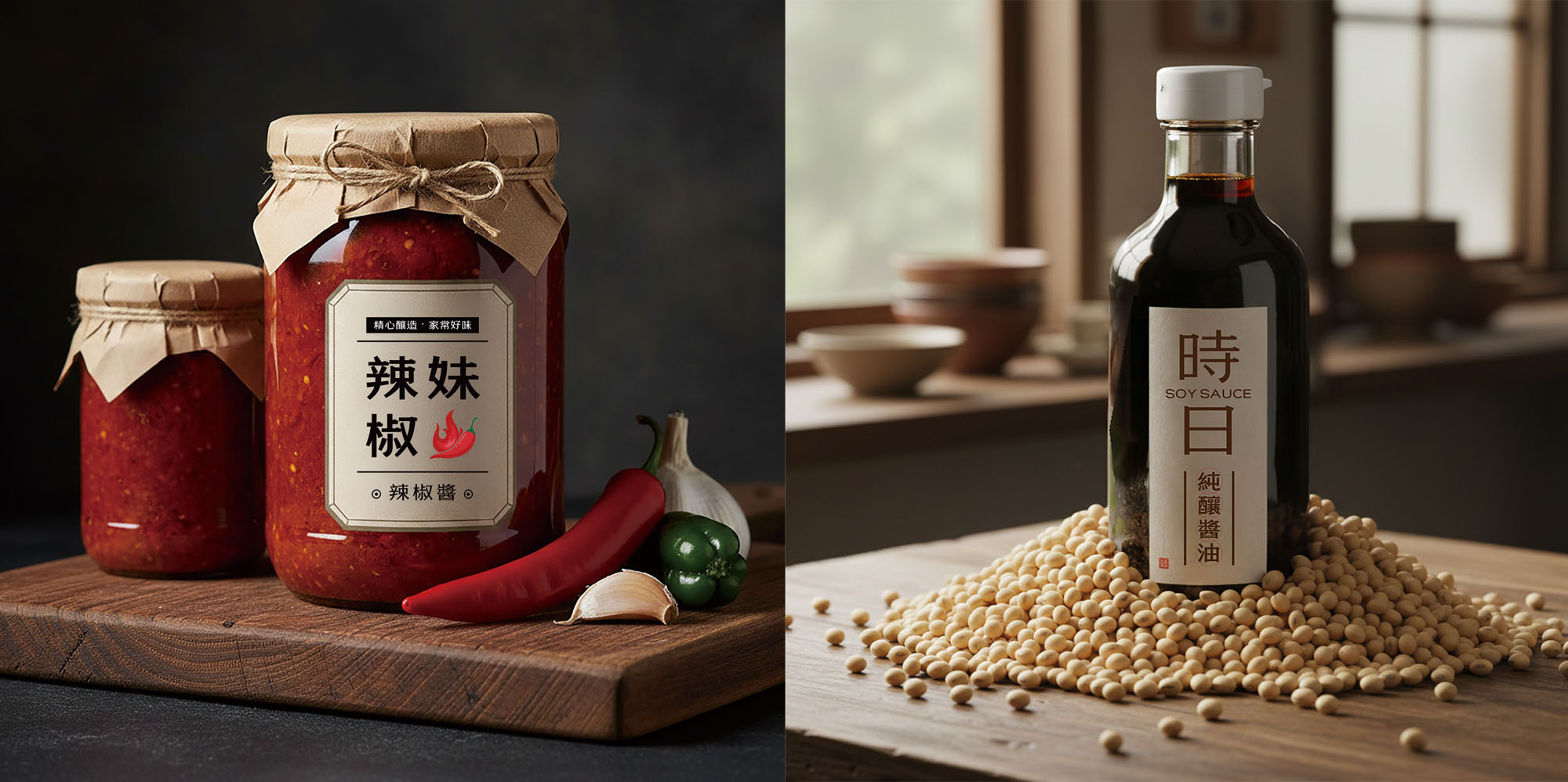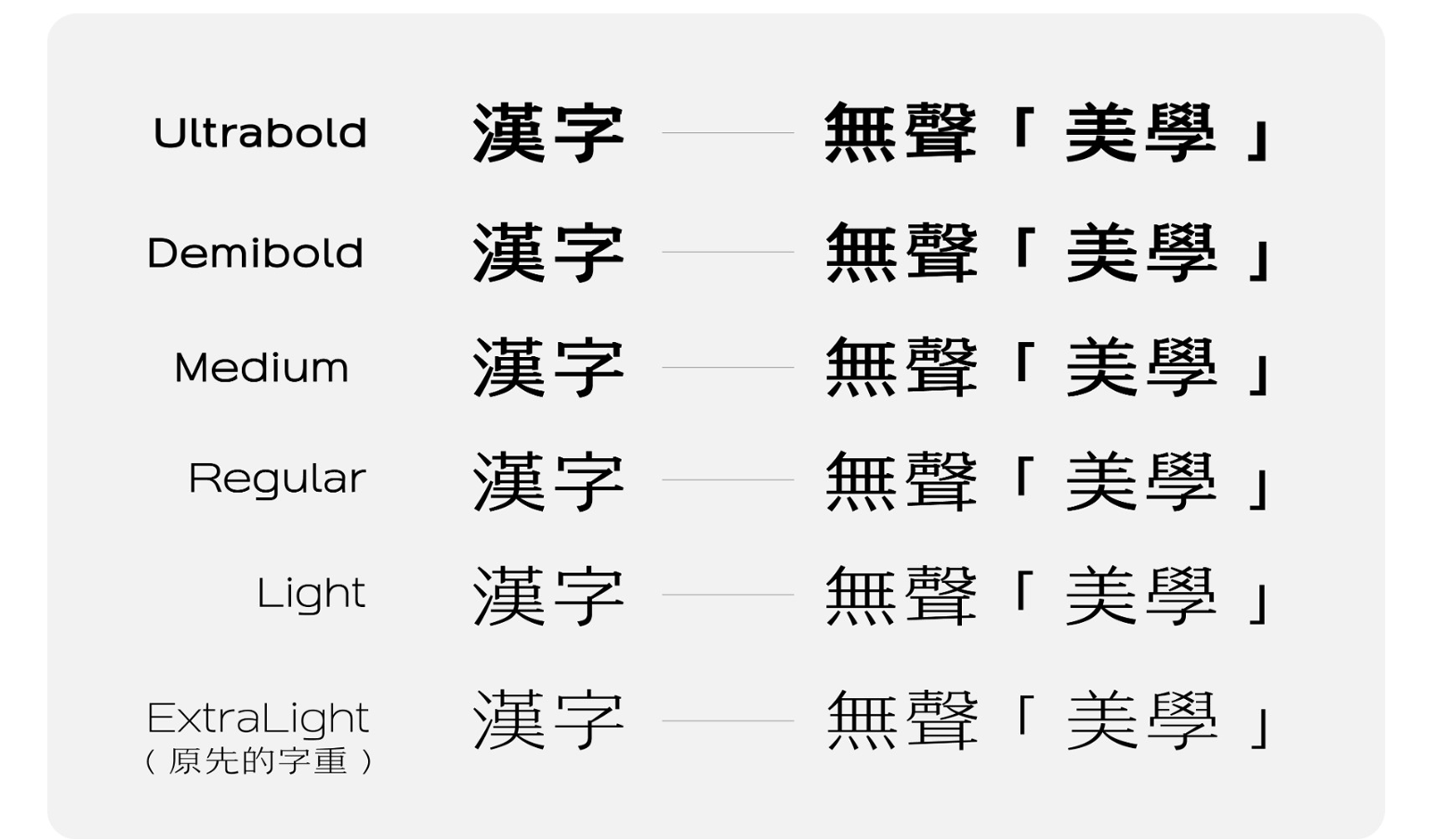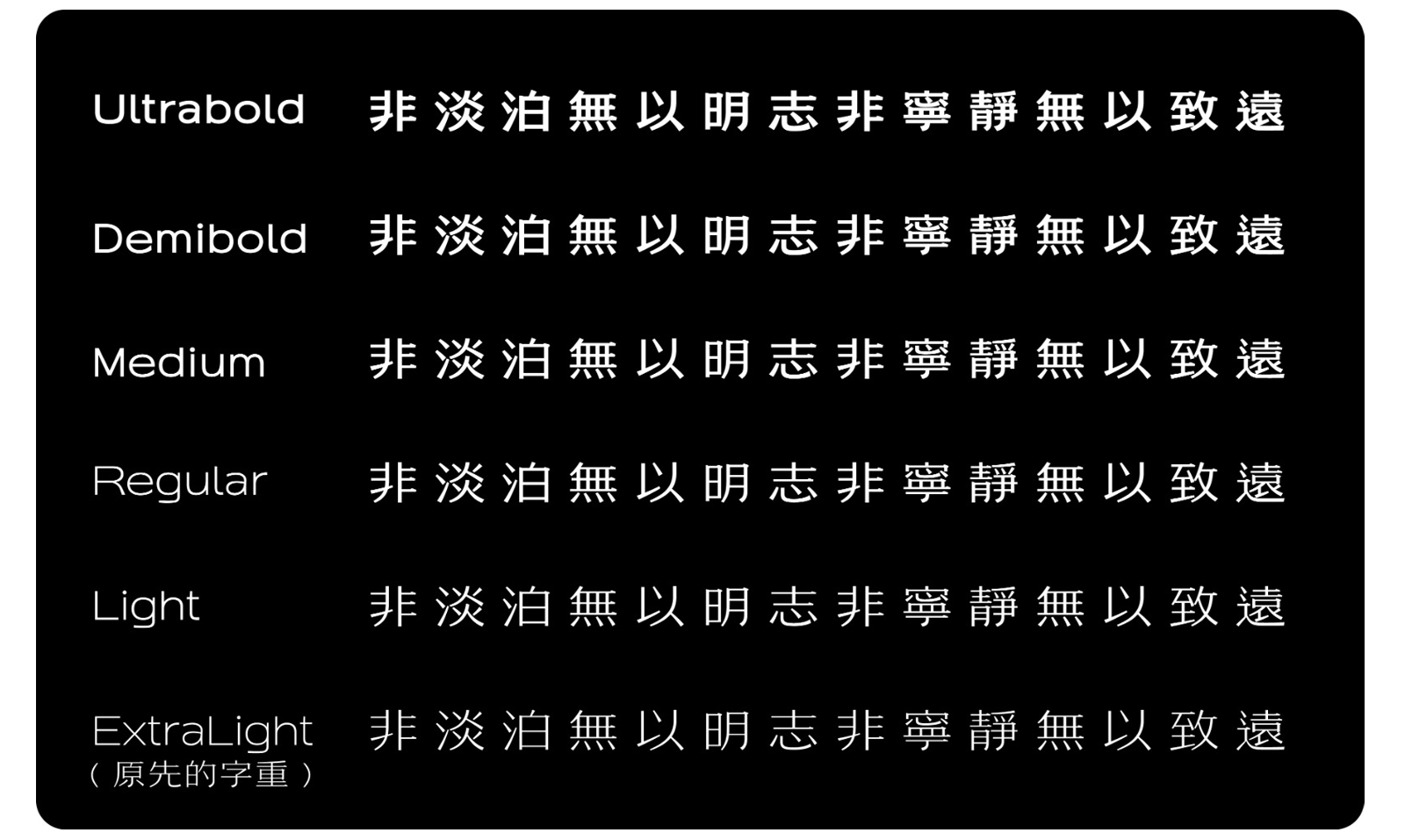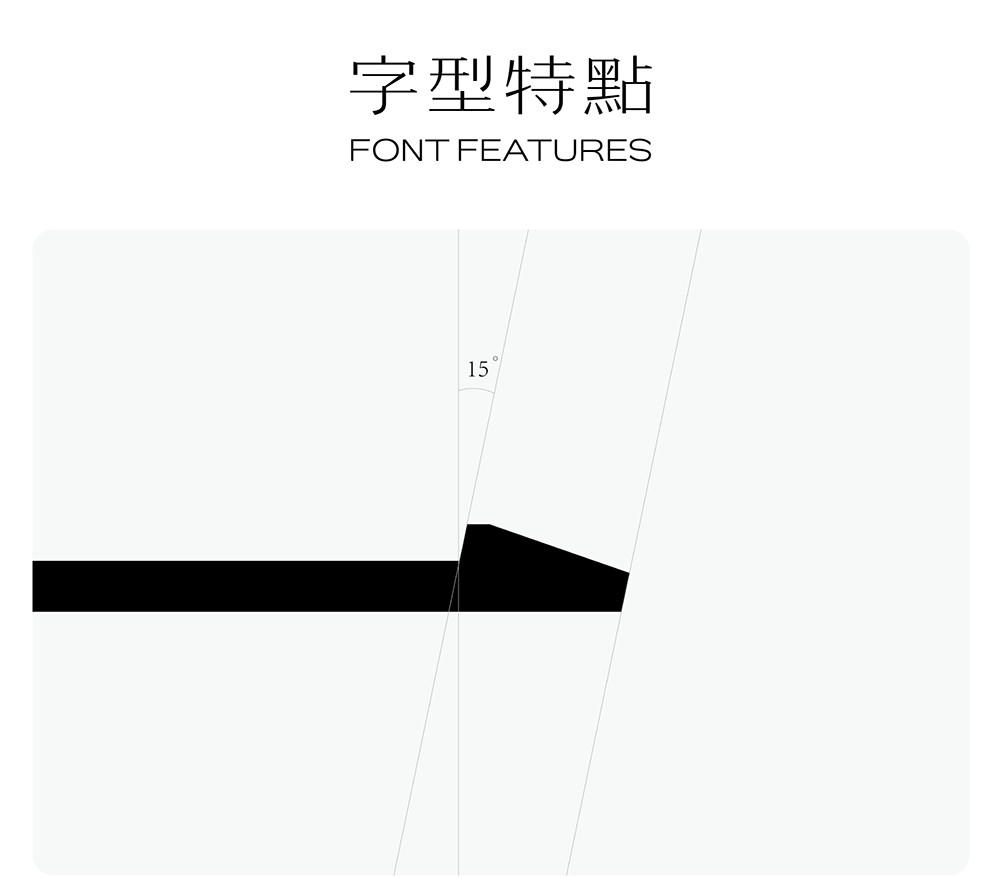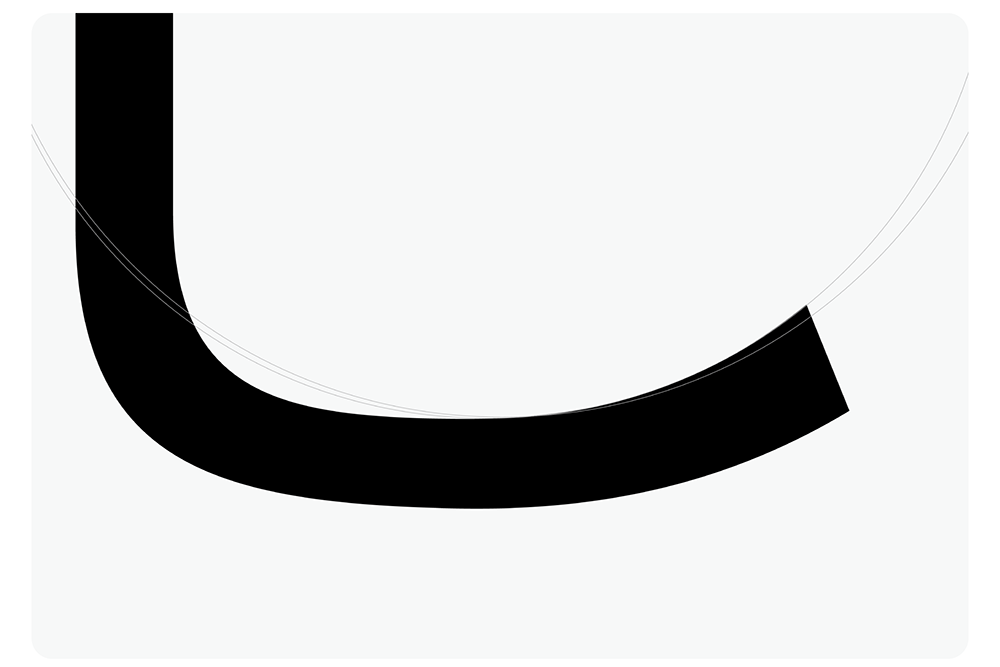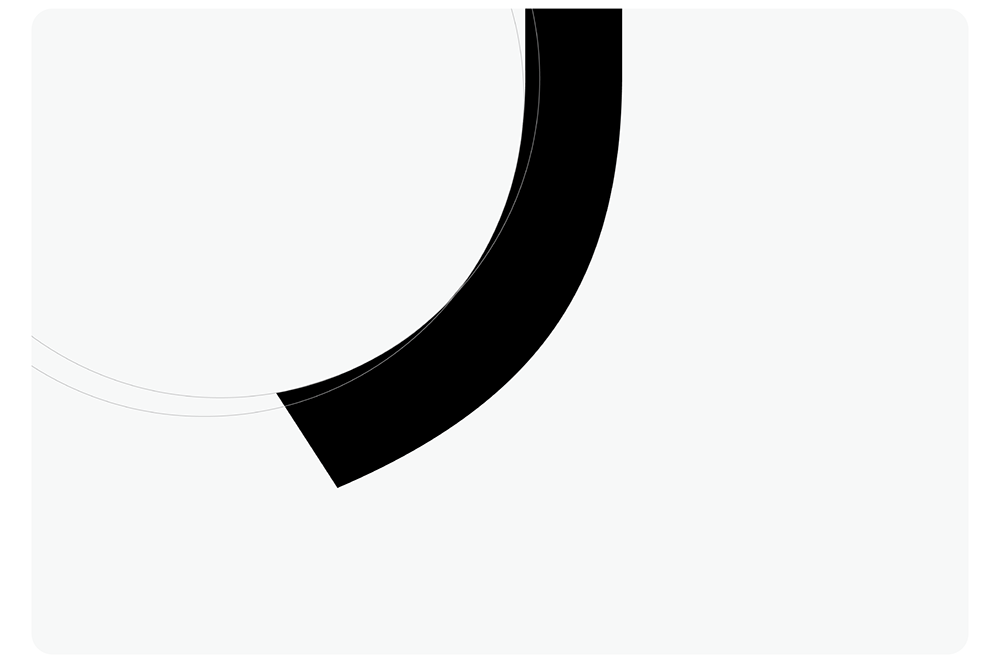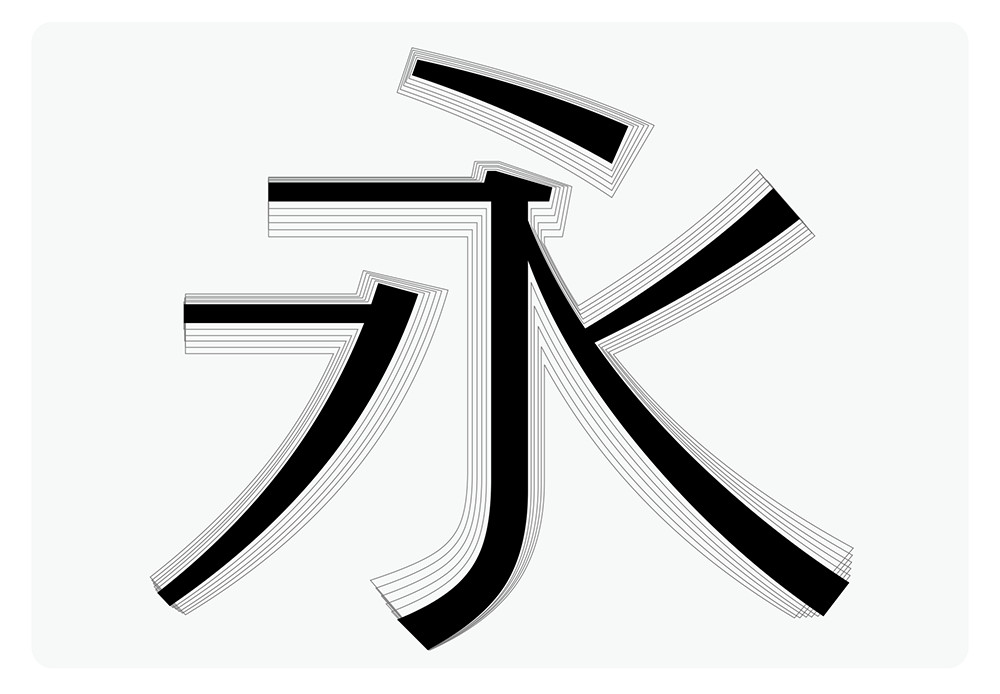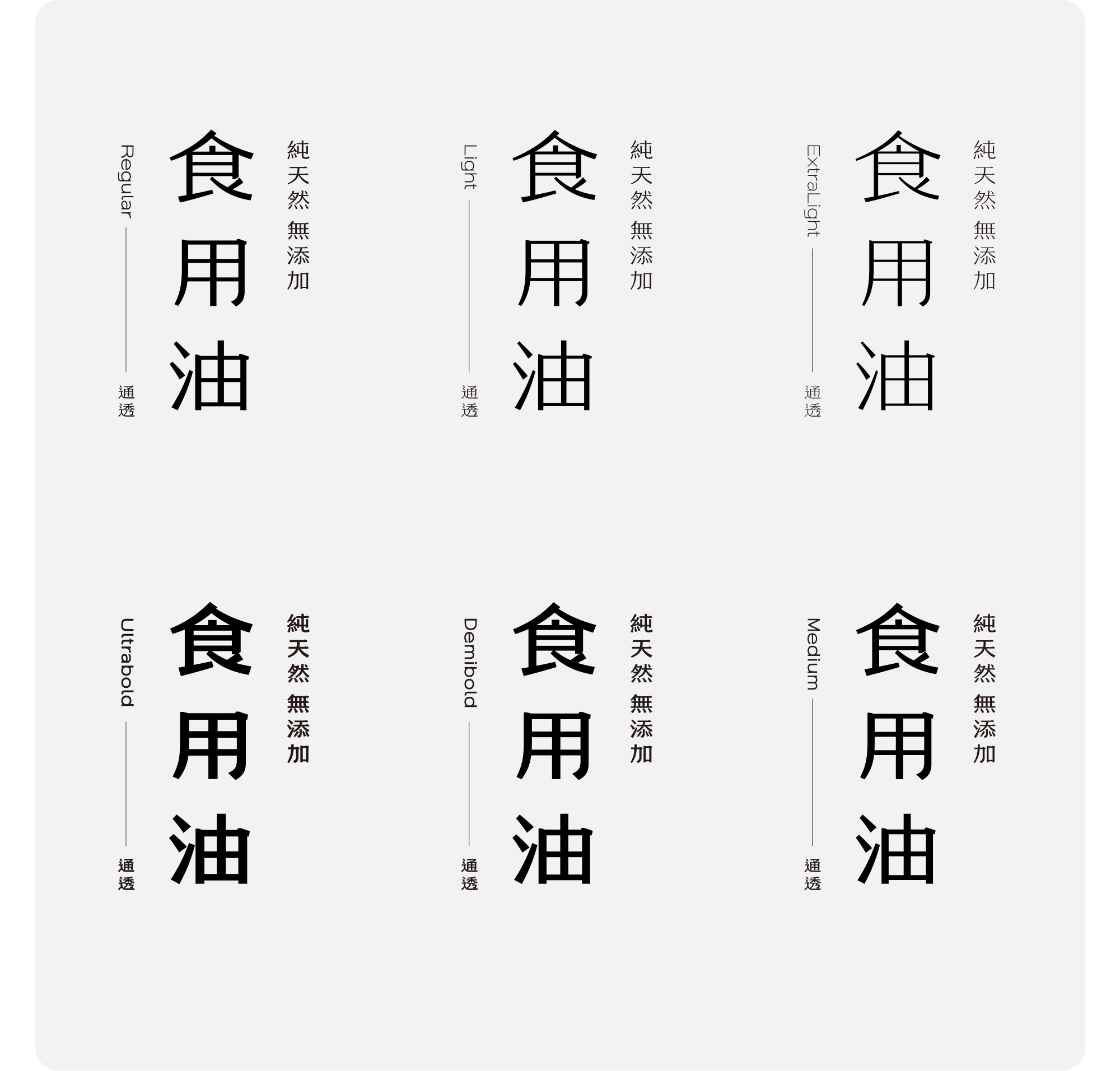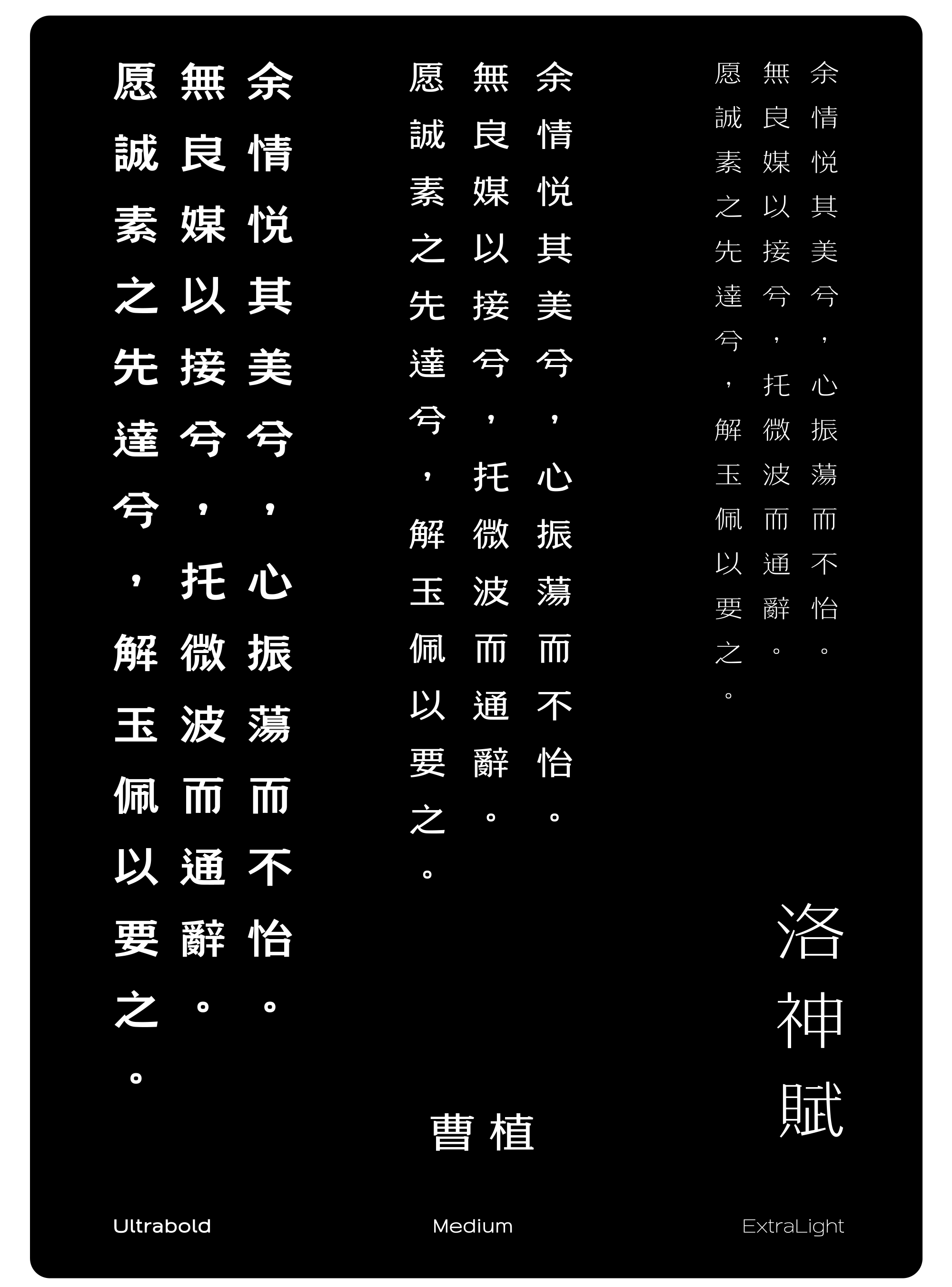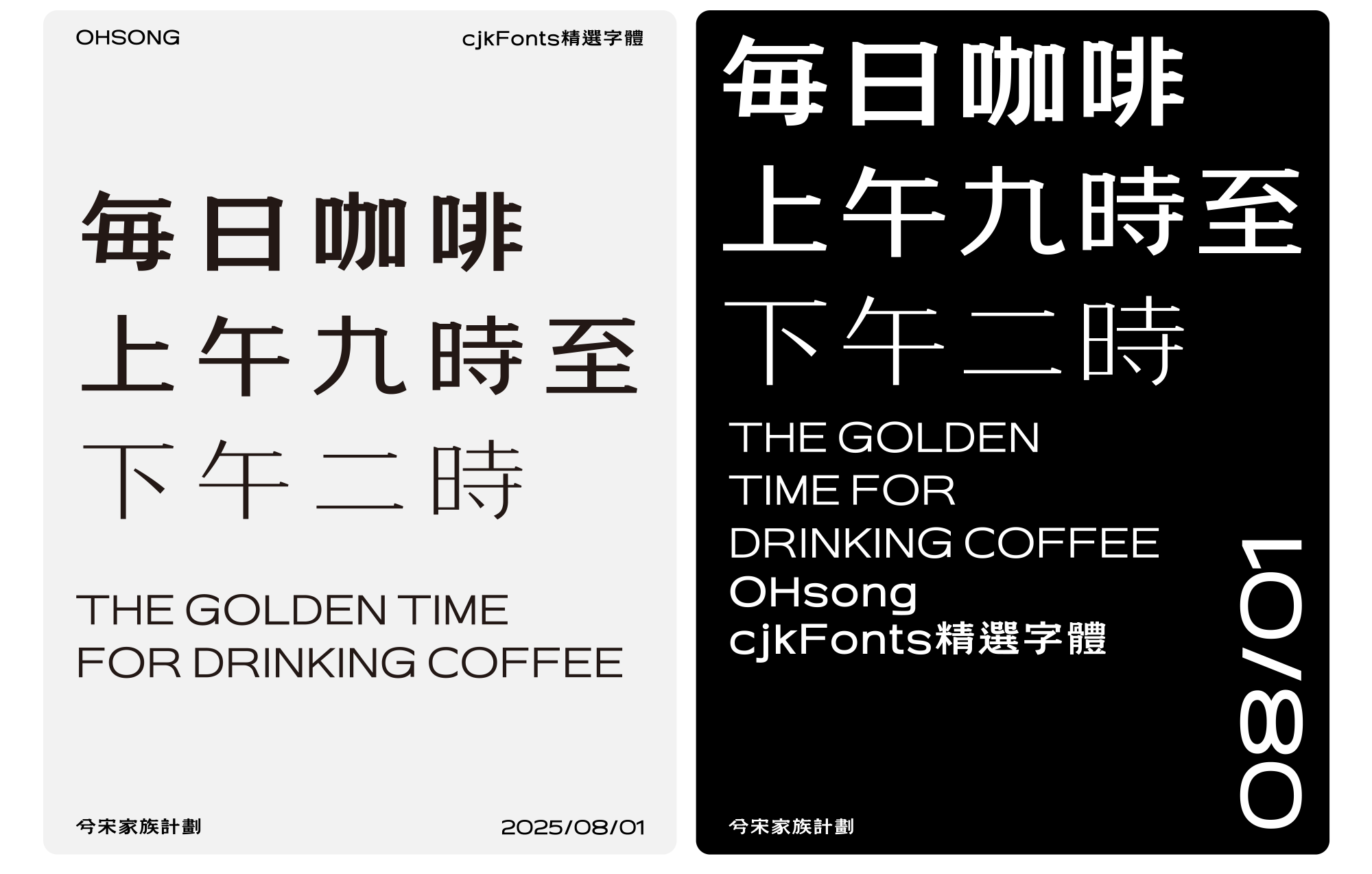
兮宋字體眾籌計劃:讓優雅的中文字體綻放完整光芒!
大家好!我們是兮宋字體的設計團隊,一群熱愛漢字藝術與文化的創作者。致力於製作一套融合傳統宋體經典與現代簡約的中文字體。今天,我們興奮宣布「兮宋字體擴充計劃」正式啟動!透過眾籌,我們希望集結社群力量,讓兮宋從單一字重蛻變成完整家族,滿足書籍、網頁、海報到品牌設計的多元需求。
兮宋的誕生:從兮宋ExtraLight開始的優雅之旅
兮宋靈感源自宋體的經典線條,注入輕盈現代感,讓漢字如詩般流暢。目前,我們已完成 兮宋 ExtraLight(極細)字重 ——字體的堅固結構和向外舒展的筆劃表現了擁有深厚內在的優美形象,筆劃末尾的增添了自然的美。以現代的手法重新詮釋漢字之美,深受客人喜愛。但一套偉大的字體需要多樣字重來適應不同情境:兮宋 ExtraLight 雖美,卻缺粗體的張力與中間字重的平衡。這就是我們發起眾籌的初衷——讓兮宋成為你的設計利器!
共 5 款字重
A TOTAL OF 5 FONTS
原先的 ExtraLight 基礎上新增了 5 個字重
• Ultrabold — 最粗字重,適合標題與強調
• Demibold — 半粗字重,兼具可讀性與強調效果
• Medium — 中等字重,適合小標題或正文
• Regular — 常規字重,最常用於正文
• Light — 輕字重,適合副標題或設計感文字
製作目標: 約9000個字(包括歐文、日文假名及其它常用字符)
字體的堅固結構和向外舒展的筆劃表現了擁有深厚內在的優美形象,筆劃末尾的增添了自然的美。以現代的手法重新詮釋漢字之美。